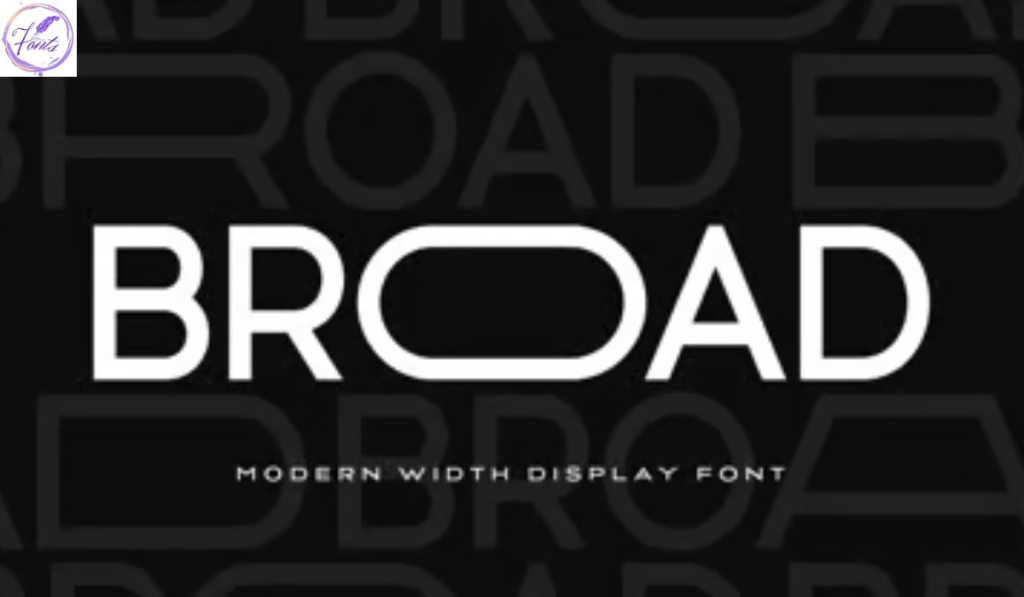
Broad fonts việt hóa
Tác giả: Christian Schwartz, Cornel Windlin
Ngày phát hành: 2016
Ngôn ngữ: Tiếng Việt, Tiếng Anh, và nhiều ngôn ngữ khác
Bộ Font: Broad
Phân loại: Cá tính, độc đáo
Kiểu chữ: Sans-serif, Display
Độ dày: Hairline, Thin, Light, Regular, Medium, Bold, Black
Broad fonts là một bộ phông chữ đa dạng và phong phú, được thiết kế bởi nhóm thiết kế Christian Schwartz, Cornel Windlin và ra mắt vào năm 2016. Bộ phông chữ này bao gồm nhiều kiểu chữ khác nhau, từ sans-serif hiện đại đến serif cổ điển, mang đến sự lựa chọn phong phú cho các nhà thiết kế. Broad fonts được thiết kế với mục tiêu tạo ra sự hài hòa và tính thẩm mỹ cao trong các dự án thiết kế đồ họa, quảng cáo và in ấn. Phiên bản việt hóa của broad fonts đã được tối ưu hóa, giúp người dùng tiếng Việt dễ dàng áp dụng và sử dụng một cách hiệu quả nhất.
Đánh giá broad fonts
Broad fonts đã nhận được nhiều phản hồi tích cực từ cộng đồng thiết kế. Với sự đa dạng và phong phú, bộ phông chữ này đáp ứng tốt nhu cầu sáng tạo của các nhà thiết kế, từ các dự án cá nhân đến chuyên nghiệp. Nét chữ sắc sảo, rõ ràng và dễ đọc là những điểm mạnh nổi bật của broad fonts. Đặc biệt, phiên bản việt hóa của broad fonts giúp các ký tự tiếng Việt hiển thị một cách hoàn hảo, mang lại trải nghiệm tuyệt vời cho người dùng. Broad fonts thực sự là một công cụ hữu ích cho mọi dự án thiết kế.